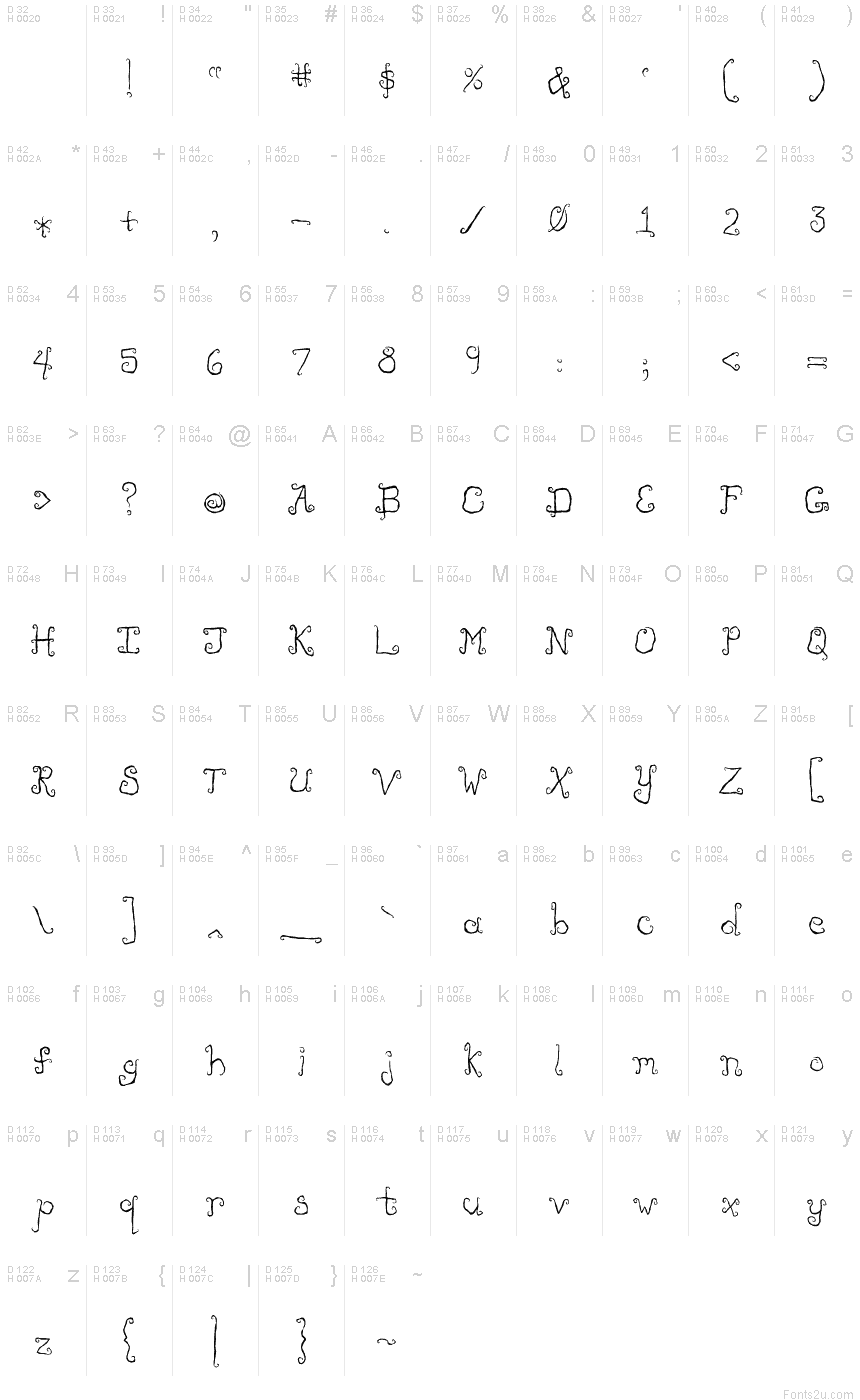
Like Cockatoos autorstwa Kevina Richeya to darmowy, kręcony font displayowy o nieco upiornym charakterze, z nitkowatymi pociągnięciami i pętelkowymi końcówkami, które nadają literom wygląd jakby były rysowane ręcznie, z nutką niepokoju. Wysokie, wąskie formy i luźne spiralne loki nadają mu figlarny, halloweenowy nastrój, a nie grozę – dzięki czemu font sprawia wrażenie dziwacznego, nerwowego i lekkiego w odbiorze.
Pasuje do nagłówków plakatów, ulotek imprezowych, okładek książek, szyldów i kart tytułowych, gdzie darmowy font może wnieść kapryśną, niesamowitą nutę bez popadania w mrok. Ponieważ loki powtarzają się tak wyraziście, sprawdza się również w przypadku krótkich imion, monogramów i haseł, które mają mieć w sobie odrobinę teatralnego drżenia.
LikeCockatoos
Like Cockatoos